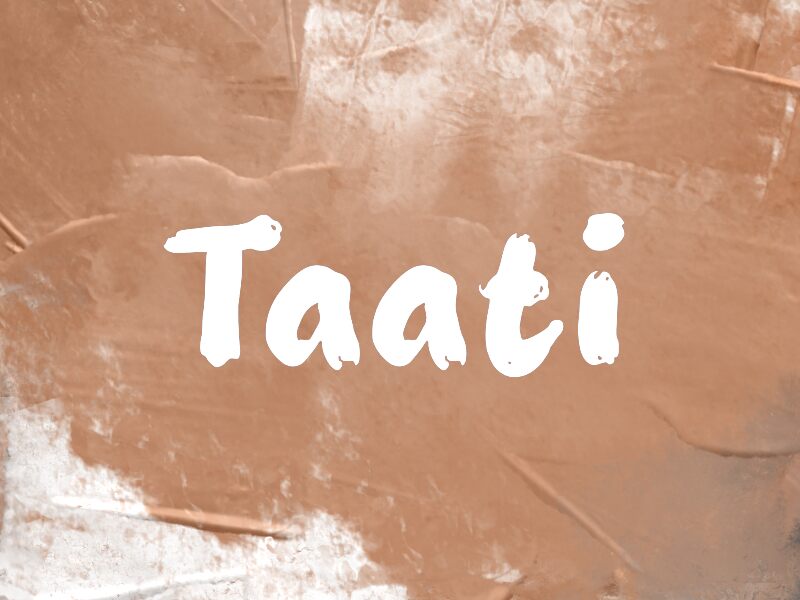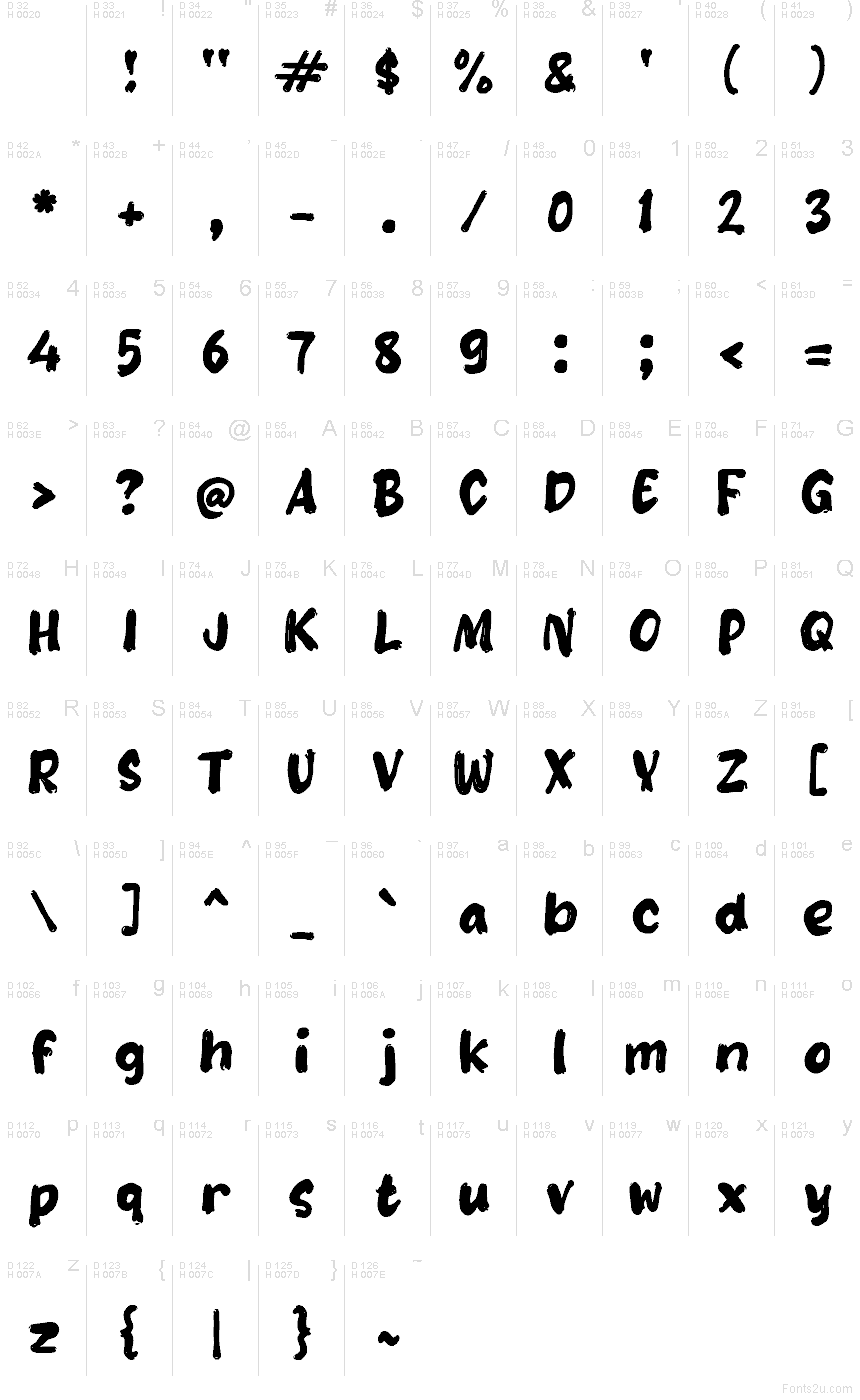
Taati od Wepfont to darmowy font pędzlowy o solidnym, ręcznie malowanym charakterze. Litery wyglądają, jakby były pełne świeżego tuszu, mają zaokrąglone końce, obłe kształty i lekko nieformalny rytm, co nadaje całości radosną, domową energię.
Świetnie sprawdza się na luźnych opakowaniach, nagłówkach plakatów, w dziecięcym brandingu, menu kawiarnianych czy grafikach do mediów społecznościowych, gdzie darmowy font powinien być przyjazny, a nie sztywny. Dzięki grubym, wyraźnym pociągnięciom Taati sprawdza się również w krótkich hasłach lub logotypach, którym chcesz nadać miękki, malarski klimat, unikając jednocześnie zbyt sterylnego efektu.
Taati
Prezentacja i próbka wizualna czcionki Taati
Mapa znaków czcionki Taati
Mapa znaków czcionki Taati: Podstawowy łaciński, strona 1
Glify czcionki Taati — Podstawowy łaciński, strona 1